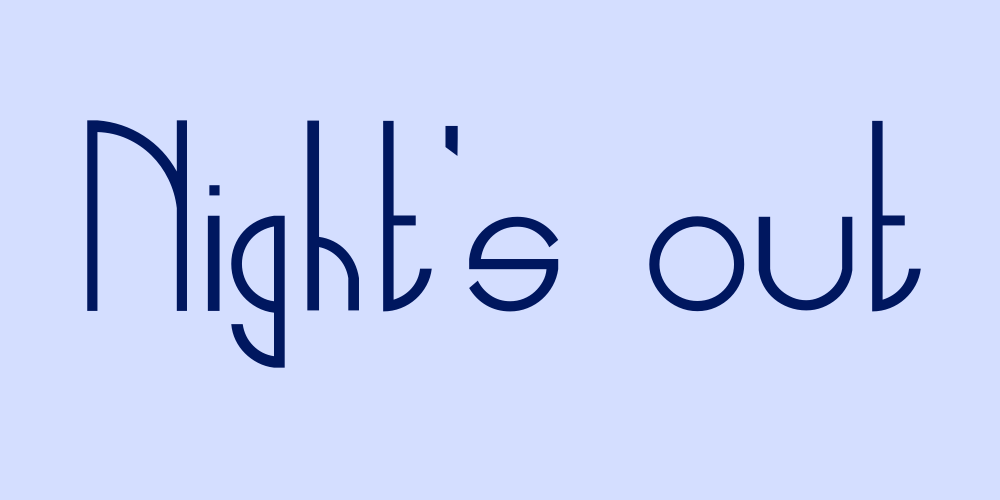
A Night’s Out é uma elegante e moderna fonte de séries sem serif criada pelo designer Hamilton. Esta fonte adere a vários estilos de design, seja para aplicativos móveis ou projetos web, oferecendo um estilo clean e contemporâneo que combina perfeitamente com as necessidades dos designers atuais. Com linhas leves e uma tipografia clara, Night’s Out é fácil de ler em qualquer tamanho e densidade. Suas formas simples mas criativas tornam-na perfeita para trabalhos profissionais como portais online ou aplicativos de mídia social, proporcionando um toque moderno sem perder a sofisticação necessária. O design minimalista da Night’s Out se destaca como uma excelente opção entre as séries sem serif, oferecendo aos designers um recurso confiável e versátil para seus projetos. Com seu formato elegante e estilo moderno, é fácil ver por que esta fonte se tornou popular entre designers de todo o mundo.